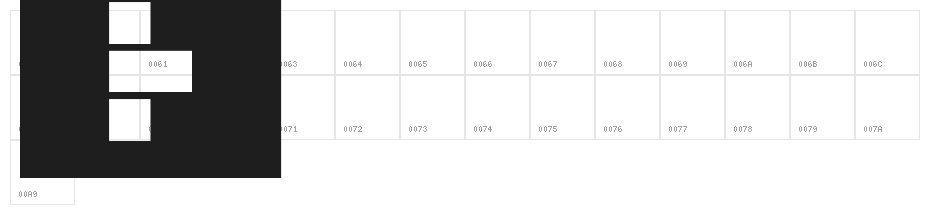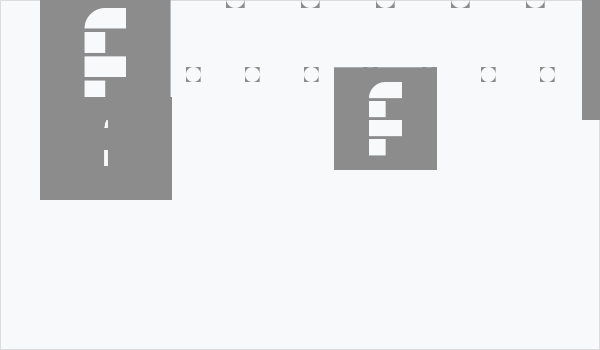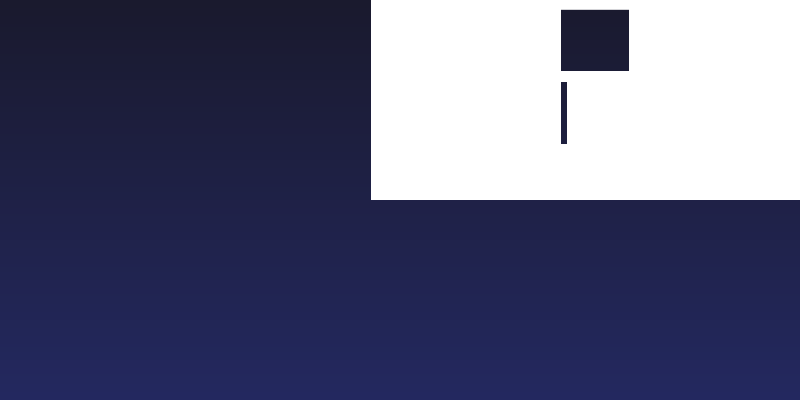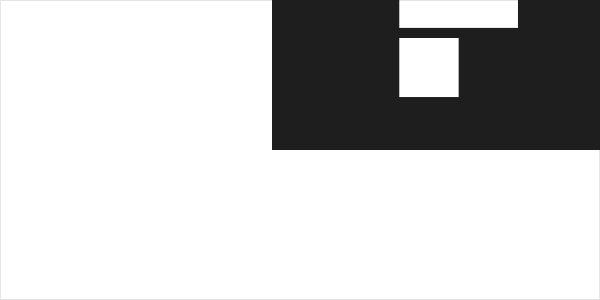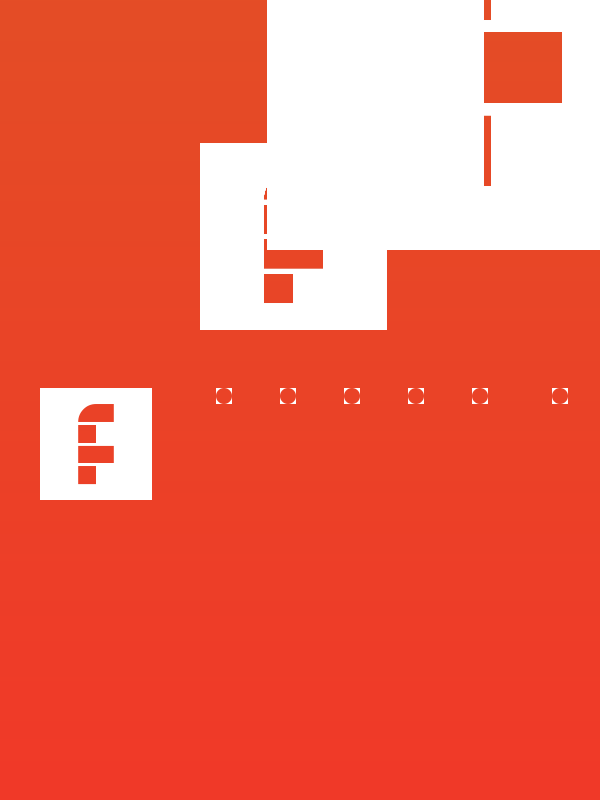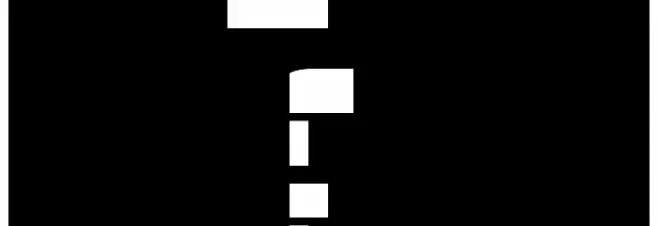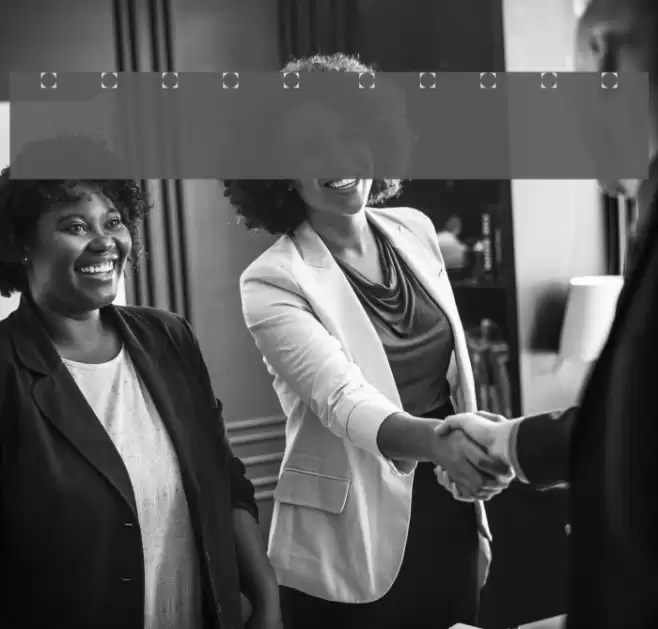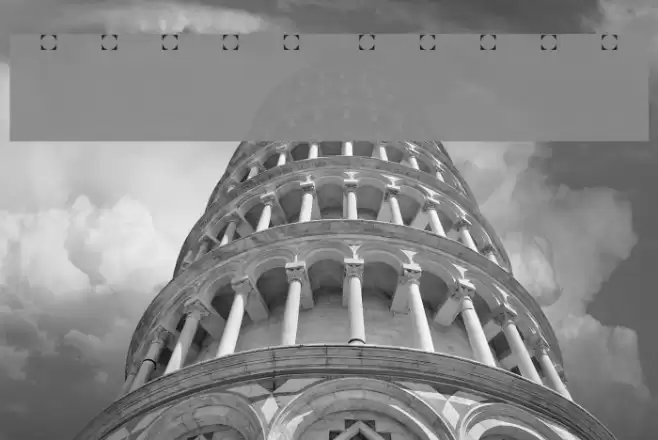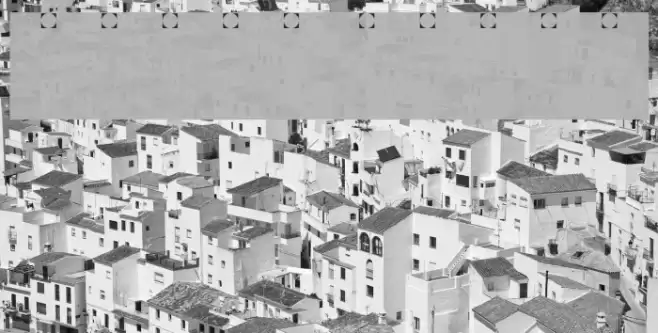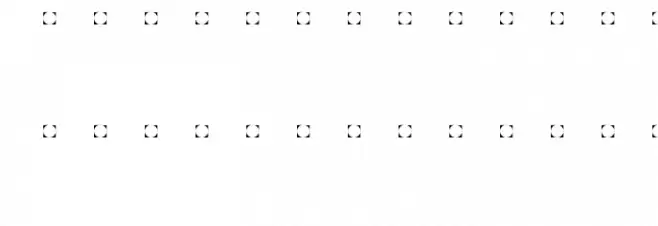
music Regular Font
| Anwendungsfall | Logos, Posters, Educational Materials |
| Vorgeschlagene Projekte | Ideal for music-themed posters, educational materials, and creative design projects that require a musical touch. |